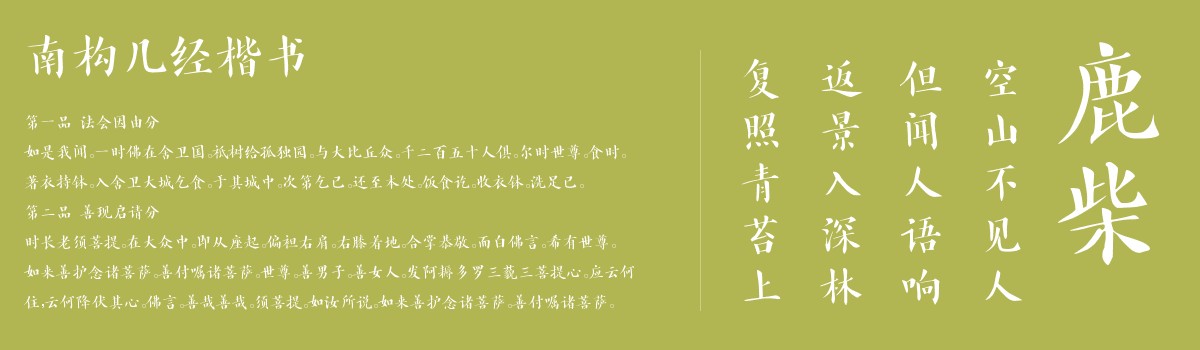
南构几经楷书
南构几经楷书是一款由字体家AI神笔造字生成的一款艺术字体,笔画端正如磐石稳立,起笔藏锋似指尖轻按宣纸,收笔利落像利刃轻划,无拖沓。横画平直如桥面,承托整体;竖画挺拔似树干,顶天立地。撇捺舒展若羽翼轻展,不张扬却见张力。转折处圆融如鹅卵石,无棱角却有筋骨。结构上,部件如精心搭叠的积木,疏密得当,重心沉稳如坐禅,每个笔画都在恰当位置,不挤不松。整体温润似暖阳拂过,摸上去平滑有厚度,力藏于内,观之端庄平和,读来清晰省力,是规整中藏着温度的美。比较适合用于艺术类装饰文字,海报、网页、广告设计,室内装饰,平面标题设计、食品包装、品牌标志等。